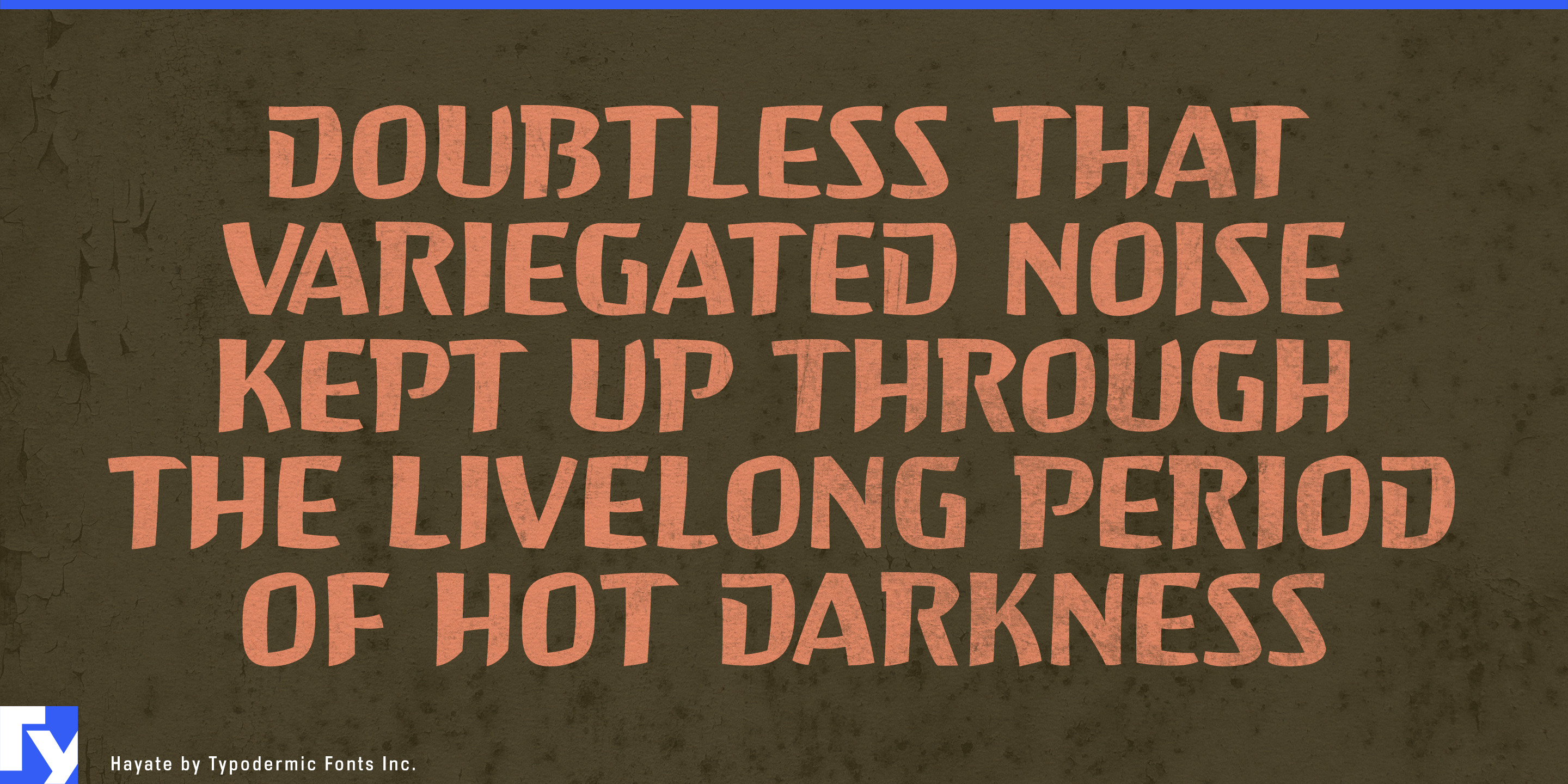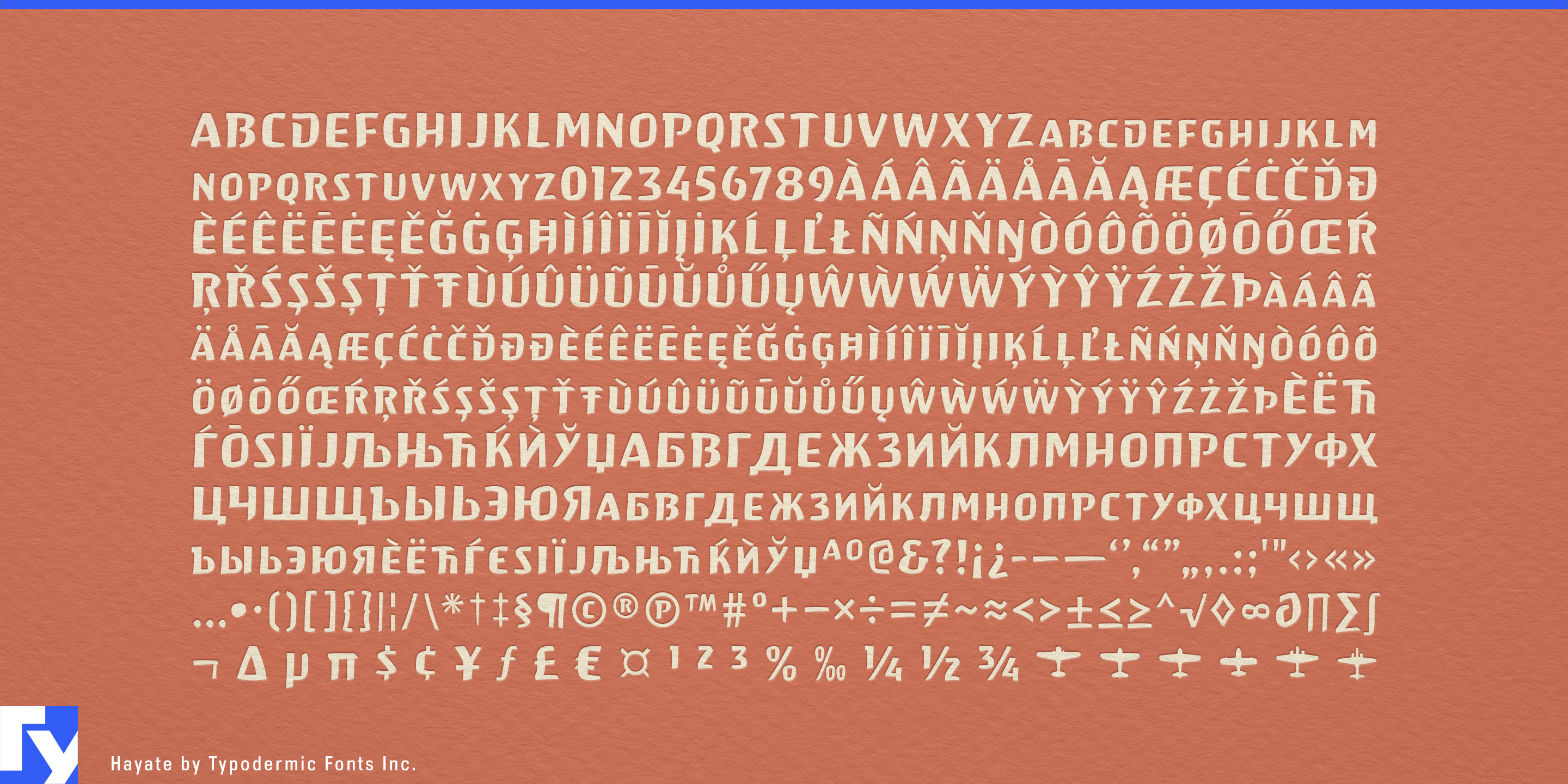
Hayate
Outdoor-Produkte werden oft in eine von drei vertrauten typografischen Richtungen gedrängt: Militärschablonen für Robustheit, nostalgische Parkbeschriftung für Tradition oder ausgefeilte geometrische Sans Serif für hochwertige technische Ausrüstung. Dazwischen bleibt eine schwierige Lücke für Geräte, die robust und doch nicht taktisch, zeitgemäß und doch nicht steril, outdoororientiert und doch nicht wie aus einer Rangerstation der 1930er-Jahre wirken sollen. Hayate füllt diese Lücke mit kompakten, kantigen Versalien, deren gekerbter Aufbau kurzen Wörtern eine behauene, praktische Qualität gibt.
Das macht sie besonders nützlich für Ausrüstung zwischen Campingbedarf und Feldtechnik. Tragbare Powerstations, Solargeneratoren, Campingkocher, Wasserfilter, Expeditionskoffer, Dachzeltsysteme und modulare Campingküchen benötigen Produktnamen, die neben Batterien, Aluminiumplatten, Formgehäusen und wetterfesten Stoffen bestehen können. Hayate kann Namen von Modellserien, Geräteplaketten, Kartons und Messeüberschriften übernehmen, ohne auf Schablonenstege, Warnstreifen oder pseudomilitärische Markierungen zurückzugreifen.
Autarke Stromversorgung und abgelegene Infrastruktur erweitern diese Rolle über die Freizeit hinaus. Solarladesysteme, tragbare Batterieverbünde, Wasseraufbereitungsgeräte, Satellitenkommunikations-Sets und modulare Feldstationen verbinden Technik mit Umgebungen, in denen Schlamm, Wetter und grobe Handhabung zu erwarten sind. Hayate kann dem Erscheinungsbild seine praktische Outdoor-Ebene geben, während eine klare Sans Serif technische Daten und Texte der Benutzeroberfläche übernimmt.
Dieselbe Sprache passt zu Forsttechnik und professionellen Holzbearbeitungsmaschinen. Mobile Sägewerke, Holzspalter, Baumpflegeausrüstung, Werkzeuge für den Holzrahmenbau und schwere Werkstattmaschinen können Hayate für Produktliniennamen, Geräteaufkleber, Messegrafiken und Verpackungen nutzen. Ihre konstruierten Formen lassen an geschnittenes und geformtes Material denken, statt an die beliebige Aggressivität einer taktischen Schablonenschrift.
Camping und Gastgewerbe im Outdoor-Bereich bleiben ein naheliegendes Gebiet, besonders Berghütten, Hüttenanlagen, Wander- und Trailzentren, Outdoor-Sauna-Retreats und zeitgemäße Campingplätze. Hayate kann Hüttennamen, Aktivitätstafeln, Ausrüstungsverleihbereiche und kompakte Wegweisung übernehmen, ohne das ganze Erscheinungsbild in nostalgische Nationalparkgestaltung zu zwingen.
Mit Blick auf die frühen 2030er-Jahre passt Hayate auch zu Outdoor-Infrastruktur rund um Reparatur, Naturschutz und erneuerbare Energie: solarunterstützte Einrichtungen an Wanderwegen, Basen zur Wiederherstellung von Lebensräumen, Mobilitäts-Reparaturstationen und abgelegene Forschungscamps. Kurze Beschriftungen wie FIELD STATION, TRAIL CREW und SOLAR BASE nutzen ihren kompakten Aufbau besonders gut.
Für Fernseh-, Streaming- und Spielegrafiken bietet Hayate eine Alternative zur üblichen Survival-Show-Schablone. Expeditionsdokumentationen, Serien über Bauprojekte in abgelegenen Gebieten, Overlanding-Sendungen, Technikprojekte in der Wildnis und Outdoor-Wettbewerbsformate können sie für Titel, Ortskarten, Aufgabennamen und Ausrüstungsgrafiken nutzen, ohne jede Aktivität wie einen Militäreinsatz aussehen zu lassen.
- Erstveröffentlichung
- 2007
- Schriftschnitte
- 1 Schriftschnitt
- Klasse
- Serifenlos
- Kantig
- Groß- und Kleinschreibung
- Versalien
- Schriftsysteme
- Lateinisch, Kyrillisch
- Einsatzbereich
- Displayschrift
- Merkmale
- Abgenutzt